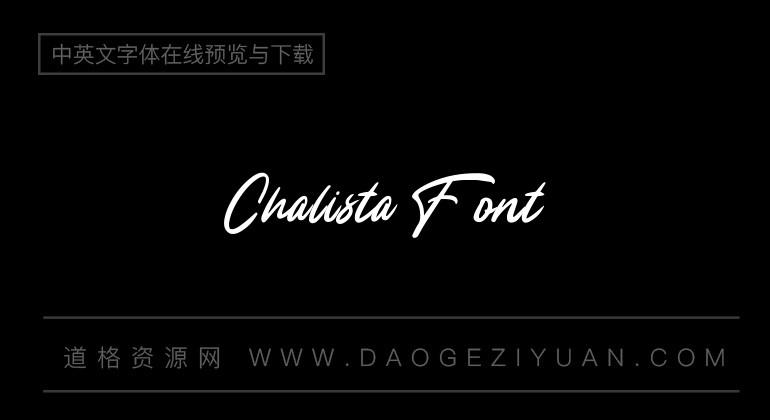
Chalista Font
Chalista Font 是一款优美的手写字体,它具有典雅、优美、流畅、和谐的特点。该字体的笔画圆润、线条流畅,给人以舒适的视觉感受。此外,Chalista Font 字体还具有多种字型,包括常规字体、粗体、倾斜体等,可供用户选择。该字体适用于各种设计场景,例如海报、卡片、书籍、标志等。如果您正在寻找一款优美、流畅的手写字体,那么 Chalista Font 将是一个不错的选择。
Chalista Font是一款非常不错的手写艺术字体,具有很好的视觉感,适合于文化类的宣传设计、商业类品牌的广告和产品包装设计以及个性化文字排版等较多场景。